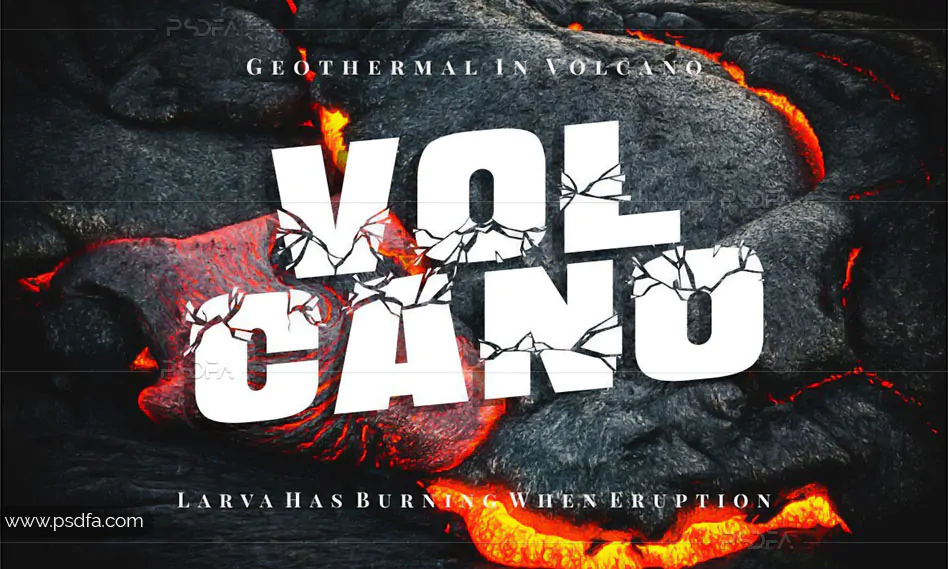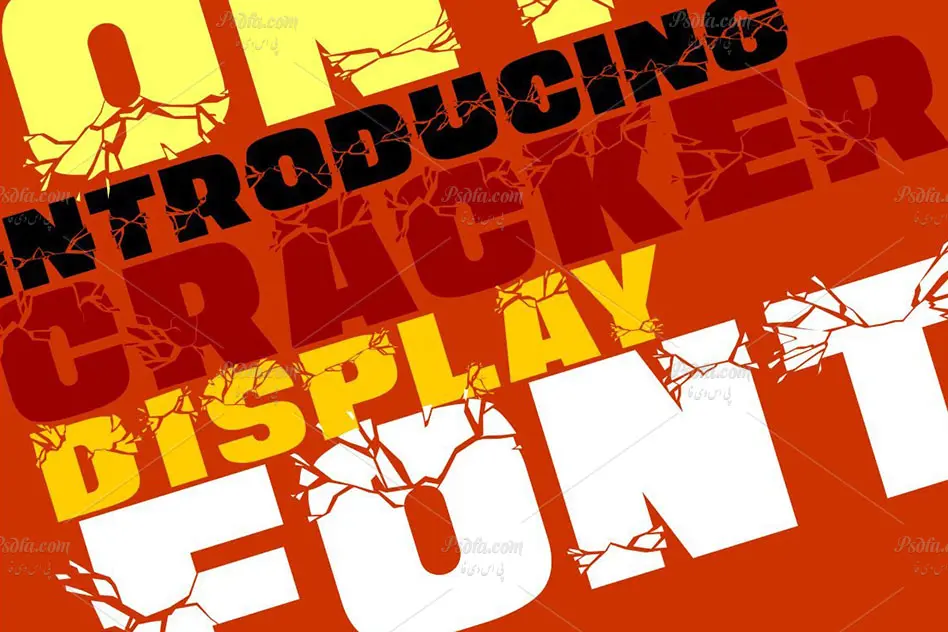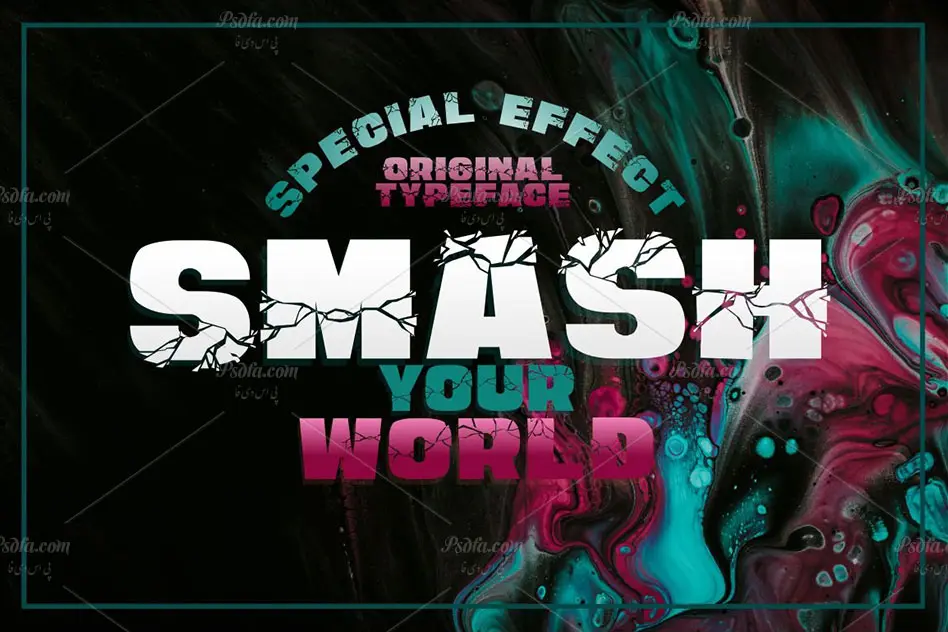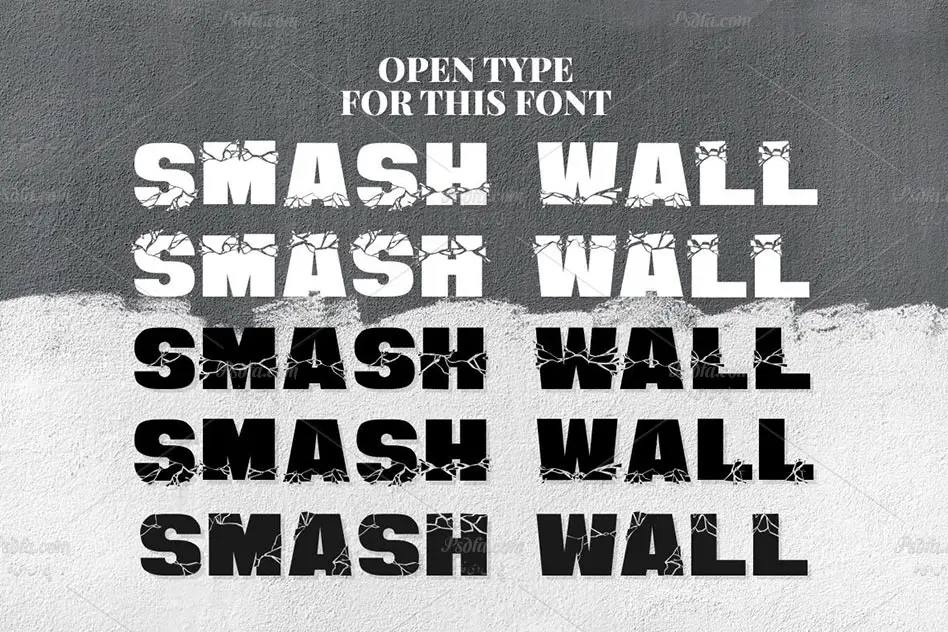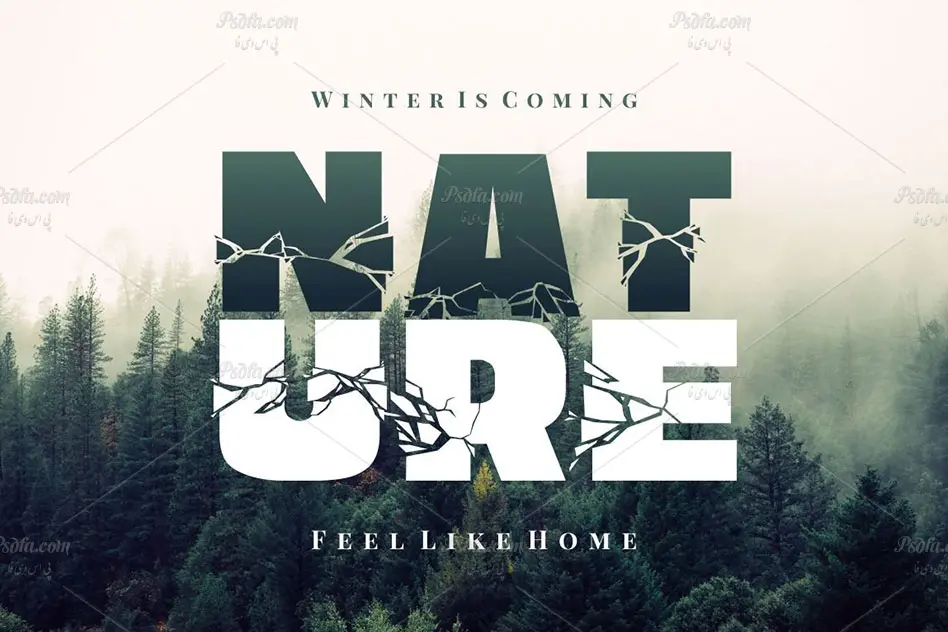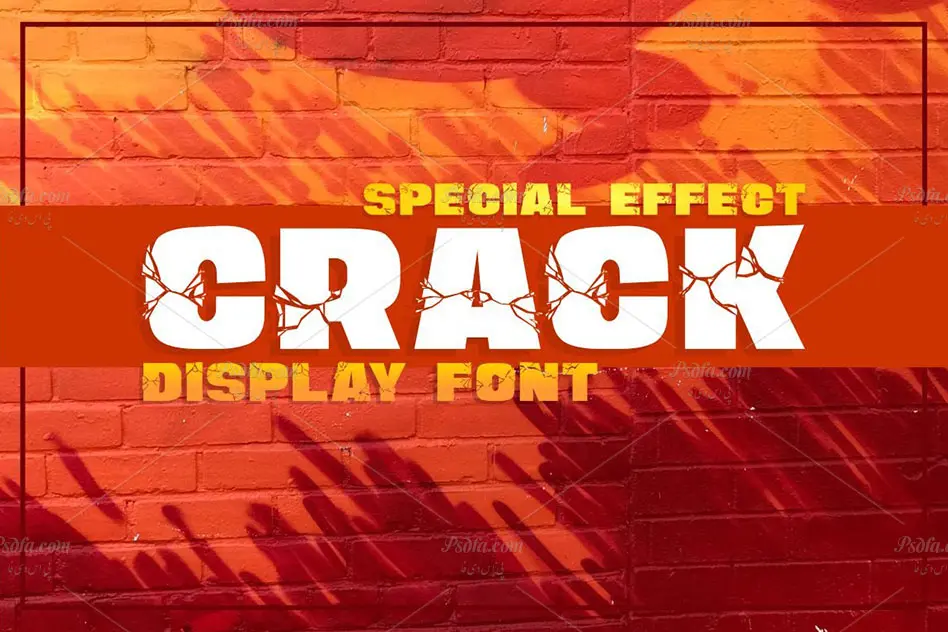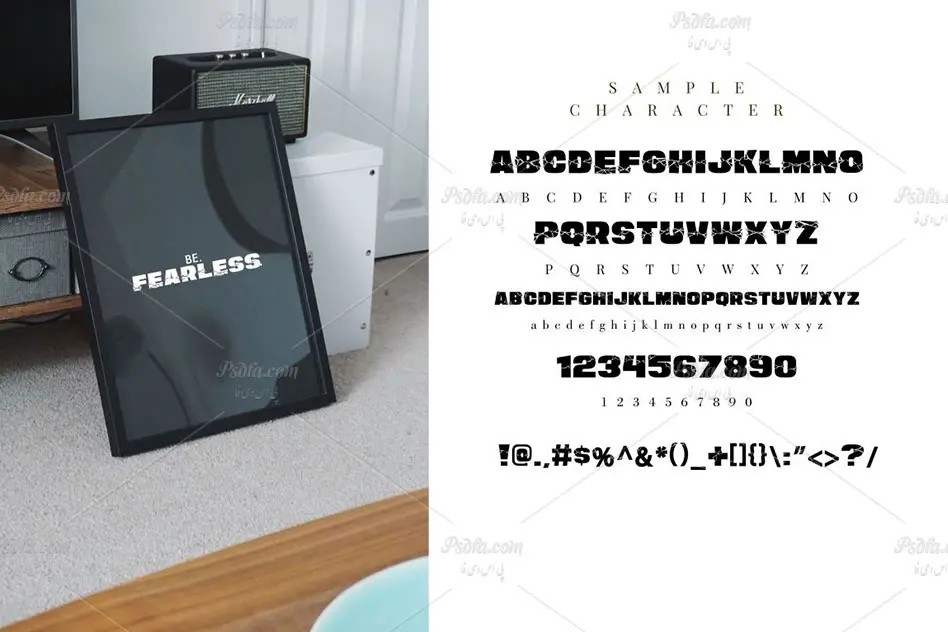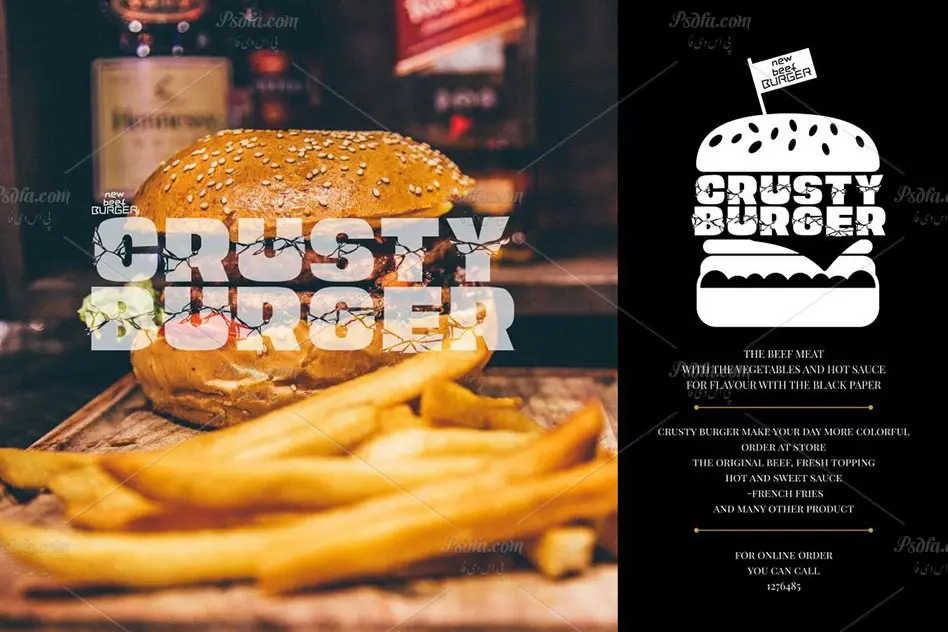
فونت انگلیسی ترک خورده
در این مطلب شاهد فونت انگلیسی ترک خورده و فوق العاده زیبای Smash Wall مناسب جهت استفاده در طرح های گرافیکی به خصوص طراحی انواع پوستر می باشید. این فونت زیبا در قالب فایل های ttf , otf و woff بر روی سایت بارگذاری شده است که با نصب یکی از دو فرمت ttf یا otf در پوشه فونت های سیستم قادر به استفاده از آن در تمام نرم افزارهای گرافیکی خواهید بود. فونت Smash Wall در وزن معمولی (Regular) طراحی شده است که از آن می توان در تیتر و عناوین طرح های گرافیکی همچون طراحی انواع پوستر ، بروشور ، کارت ویزیت ، تراکت ، بنر و … استفاده نمود. همچنین از فرمت Woff این فونت نیز می توان در طراحی سایت و یا صفحات وب استفاده کرد.